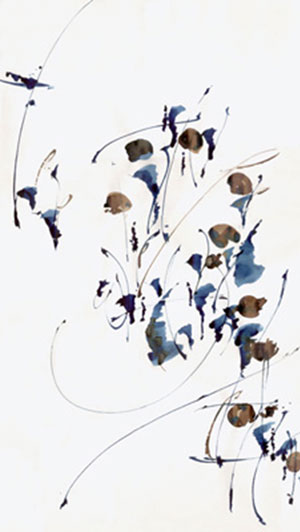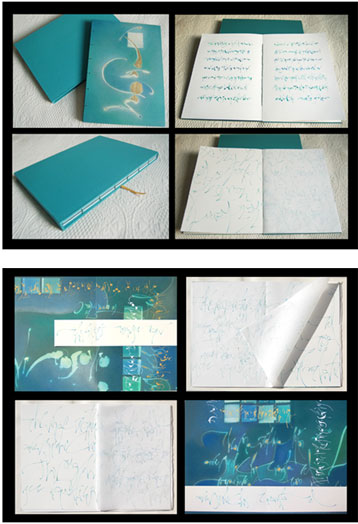
Entrevista a Marina Soria
¿Quiénes fueron tus maestros, tus referentes?
Tuve muchos maestros a lo largo de mi formación. No sé si influyeron en mi obra artística directamente pero sí en mi percepción del mundo de las artes, el diseño e, incluso, la vida.
La primera, mi abuela, una mujer llena de energía y creatividad desde todo punto de vista.
De la Escuela de Bellas Artes recuerdo con particular afecto a Bedoya, profesor de Historia del Arte; de la Escuela Panamericana del Arte, donde me formé en diseño gráfico: (Alfredo) Saavedra y (Félix) Lentino. De mi época de taller: el pintor Héctor Medicci.
Primera marca caligráfica.
Escuela Panamericana de Arte,
1987. |
El péndulo II, en el taller de Héctor Médicci, 1992. |
Me inició en la caligrafía Carol Johnson, calígrafa norteamericana que dio un seminario la FADU/UBA, en 1990. Pero a quien considero mi referente y más admirado maestro es Thomas Ingmire, calígrafo norteamericano que se dedica a la investigación y la enseñanza de la caligrafía experimental. (Para más información ir a www.scriptsf.com, www.thomasingmire.com)
Flores azules, realizado en el taller de Thomas Ingmire, 2004.
Realicé cursos con los calígrafos Brody Neuenschwander, Sheila Waters y Ewan Clayton; mis referentes también lo son los grandes calígrafos y artistas orientales.
En este último período debo mencionar a mi profesora de sumi-e*, Cristina Coroleu.
* También llamada Suiboku; técnica japonesa de dibujo monocromático en tinta
Ceibo, trabajo de sumi-e, 2008.
Invisible to the eye, libro tipo serpentina de 12 hojas, 2005.
¿Cuándo consideraste que podías llamarte calígrafa? ¿Hay un momento identificable en el que se haya dado ese “click”?
Aún hoy no sé si puedo hacerlo; creo que me falta un siglo de conocimientos y de práctica porque la ejercitación diaria durante años es la que hace a un buen calígrafo. Prefiero describirme como una artista plástica que aplica la caligrafía en todas sus formas.
En estos 28 años de trabajo, no he tenido una práctica suficiente en la disciplina de la caligrafía, sí le he dedicado tiempo a la experimentación y a fundir todos mis conocimientos previos en ella. Sí, hubo un momento, en 2007, en que me dije “pertenecés”. Recibí ese año una mención de manos de Thomas Ingmire y de Maureen Squire, en el marco del concurso internacional de Caligrafía del Guilford Handcraft Center de Connecticut, EEUU. lo cual significó un gran honor para mí. Además, Thomas me dedicó unas palabras en su artículo de apertura en la revista Letter Arts Review, la más importante publicación sobre caligrafía (“…la selección final incluye algunas creaciones asombrosas. Los alfabetos de Marina Soria en todos sus trabajos son excelentes ejemplos de inventiva y expresividad.” Extracto del texto de Thomas Ingmire. Letter Arts Review), e incluso me solicitó trabajos de caligrafía experimental para incluirlos en el segundo número de su revista Codicci, aún sin publicar.
Life force, libro, 2005/2006.
Siendo diseñadora gráfica ¿qué vínculos observás entre la práctica de la caligrafía y la del diseño? ¿Se potencian, se complementan?
Teniendo una formación inicial como artista plástica, luego como diseñadora gráfica y, finalmente, como calígrafa yo diría que todo suma. Las diferentes disciplinas e incluso las experiencias de vida moldean a un ser humano más interesante, con más cosas para decir y mejores herramientas para comunicar su mensaje.
¿Debería la caligrafía ser parte de la formación académica del diseñador gráfico? ¿Por qué?
Personalmente creo que sí. Siendo profesora de Tipografía dediqué el primer cuatrimestre completo a la introducción en el mundo de la caligrafía y al aprendizaje del alfabeto “fundacional” de Edward Johnston. Si bien en ese momento los alumnos me odiaron, creo que con el transcurrir del año lo valoraron ya que muchos de ellos aplicaron la caligrafía a sus proyectos finales.
Porque el conocimiento de la estructura, proporción y forma de construir las letras es una parte importantísima de la formación de un diseñador gráfico actual. Entender las nociones de ductus (cantidad de trazos, orden y dirección con los que se construye una letra) y la consistencia de un sistema de códigos (llámese alfabeto) solo pueden ser comprendidas y aprendidas si se transita la experiencia caligráfica. Estos contenidos aportan sólidos conocimientos a la hora de diseñar fuentes y para la futura experimentación.
Trabajos de alumnos, FADU, UBA, 1998
¿Qué pensás de la vertiente que separa el hand-writing (escritura manual) de la caligrafía (reproducción de formas clásicas de escritura)?
Son todas vertientes de un mismo recorrido. Todas las alternativas deben ser estudiadas para lograr conclusiones propias, sin importar el orden desde un punto de vista formal y experimental.
¿Cuál es el valor de la experimentación en la caligrafía? ¿Vale todo?
Sí, para mí vale todo. Hay que probarlo todo para poder evaluarlo y eventualmente descartarlo. Lo que hoy no funciona puede ser la idea genial de mañana. Yo tengo la firme convicción de que el artista se adelanta a su época y a su tiempo por lo cual se me hace muy difícil juzgar qué está bien y qué está mal, el tiempo lo dirá… Por ahora, y para mí, vale todo aunque hoy no lo comprenda.
La aplicación de la caligrafía al diseño de marcas le da cierta “utilidad” económica que hace que prolifere el recurso aún a riesgo de ser aplicado poco criteriosamente ¿Qué valor agregado le otorga a una marca el ser caligráfica?
El valor de ser única y original; de ser diseñada para ese solo propósito y cliente. Además, es irrepetible.
¿Cuándo es pertinente y cuándo es mejor usar una tipografía existente?
Es mejor usar tipografía cuando uno busca el mayor grado de legibilidad, aunque el tema de la legibilidad esté determinado por las convenciones de la época.
Siempre hay una alternativa caligráfica o de lettering para cualquier producto o servicio salvo, por ejemplo, en señalización, en donde se busca la mayor legibilidad posible.
Con la llegada del formato OpenType, la relación entre las escrituras manuales -con sus florituras y ligaduras múltiples- y la tipografía se explota cada vez más. ¿Qué se gana y qué se pierde con el pasaje de lo manual, en tanto único e irrepetible, a lo tipográfico que, en esencia, está normalizado y estandarizado?
Ocurre eso mismo que mencionás: se pierde el carácter único e irrepetible, original, fresco y personal de lo manual.
¿Qué se gana? Una nueva tipografía para el mundo comercial; en algunos casos felizmente y en otros por desgracia.
Te interesa y explorás la unión de la caligrafía con las artes plásticas. ¿Podés contarme algo de esa parte de tu trabajo?
Es una pregunta muy difícil. A nivel mundial se discute si la caligrafía es un arte o una disciplina práctica como las artes aplicadas.
He visto a lo largo de la historia del arte cómo estas disciplinas aplicadas, en determinado momento, ascienden al rango de arte y me he preguntado qué hace que algo diseñado con carácter utilitario se transforme en una verdadera obra artística.
¿Es la técnica? En parte, pero no completamente, porque sino sólo sería artesanía. ¿Es la originalidad? Mi respuesta vuelve a ser la misma que antes, porque hay cosas muy originales y mal hechas.
En realidad, la respuesta es que son estas cosas juntas lo que hace a una obra de arte: técnica, destreza, genio e inspiración.
Como dice Eugen Herrigel en su libro “Zen en el arte del Tiro al blanco”:
” ¿Cómo se torna espiritual la destreza? ¿Cómo se convierte el dominio soberano de la técnica en el arte magistral de la espada? La respuesta es: el aprendiz lo logrará únicamente si se desprende de toda intención y de su propio yo.”
Desde mi humilde posición de artista calígrafa no puedo más que aspirar a que tanto yo como mis alumnos logremos expresar lo que hay en nuestro interior: pensamientos, sentimientos y nuestra perspectiva del mundo en el que vivimos, para lo cual necesitamos de un mensaje y de una técnica para plasmarlo de la mejor manera posible.
Probablemente este sea un camino previsible para alguien que se inició en el mundo del arte y que al formarse en el diseño buscó incansablemente una forma de hacer comulgar ambos mundos y que, finalmente, encontró en la caligrafía ese puente.
No sé si respondí a tu pregunta pero si no fuera así, me gustaría ayudar citando una de las máximas que guía toda mi obra; es de Martha Graham, famosa bailarina y coreógrafa americana:
”Existe una vitalidad, una fuerza de vida, una energía, una celeridad que a través de ti se traduce en acción, y porque sólo existe una persona como tú en todos los tiempos, esta expresión es única.
Si la bloqueas, nunca existirá por otro medio y se perderá. El mundo no la tendrá. Debes mantener este canal abierto.
No te corresponde a ti determinar cuán bueno o valioso es, o cómo se compara con las expresiones de otras personas. Está en ti en mantenerlo como propio, claro y directo.”
Para terminar, ¿qué le dirías a un estudiante de diseño?
Que estudie y practique todo lo que pueda: caligrafía, diseño, dibujo, historia del arte, artes aplicadas, fotografía, etc. Pero que además vaya al cine, al teatro, que lea, que escuche música y, sobre todo, que observe desprejuiciadamente a la naturaleza que es la mayor de las obras de arte y, en especial, al ser humano.